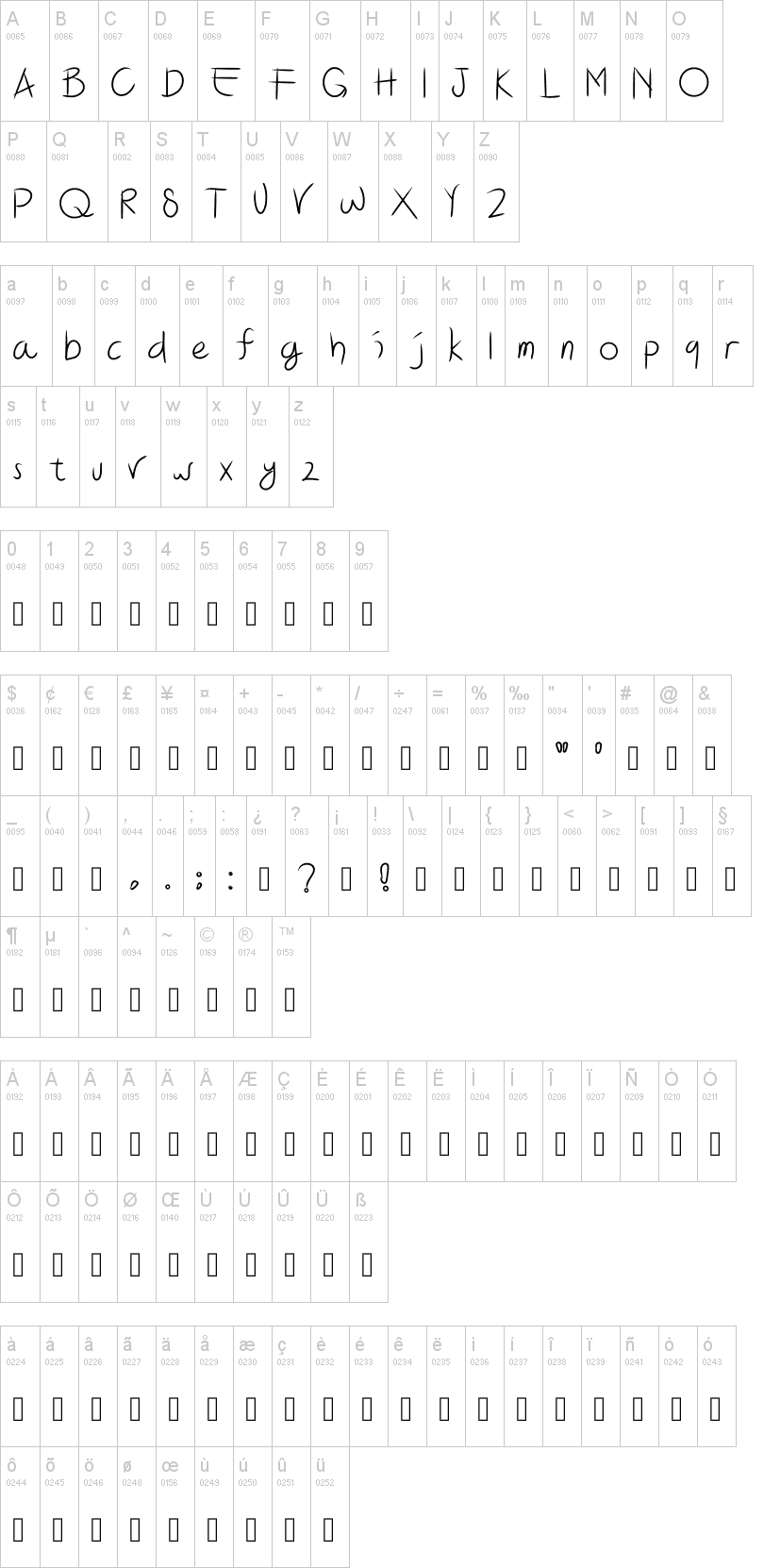
Smarts
Smarts 字体是一款多功能的字体,它可以让您在一个字体中获得多种字体风格,从而提供更多的设计灵活性。它的特点是: 1. 支持多种字体风格:Smarts 字体支持多种字体风格,包括细体、粗体、斜体等,可以满足不同的设计需求。 2. 支持多种语言:Smarts 字体支持多种语言,可以满足全球用户的需求。 3. 支持多种平台:Smarts 字体支持多种平台,包括 Windows、Mac、Linux 等,可以满足多种设备的需求。 4. 支持多种文件格式:Smarts 字体支持多种文件格式,包括 TTF、OTF、WOFF 等,可以满足不同的设计要求。
Smarts是一款非常不错的手写艺术字体,具有很好的视觉感,适合于文化类的宣传设计、商业类品牌的广告和产品包装设计以及个性化文字排版等较多场景。